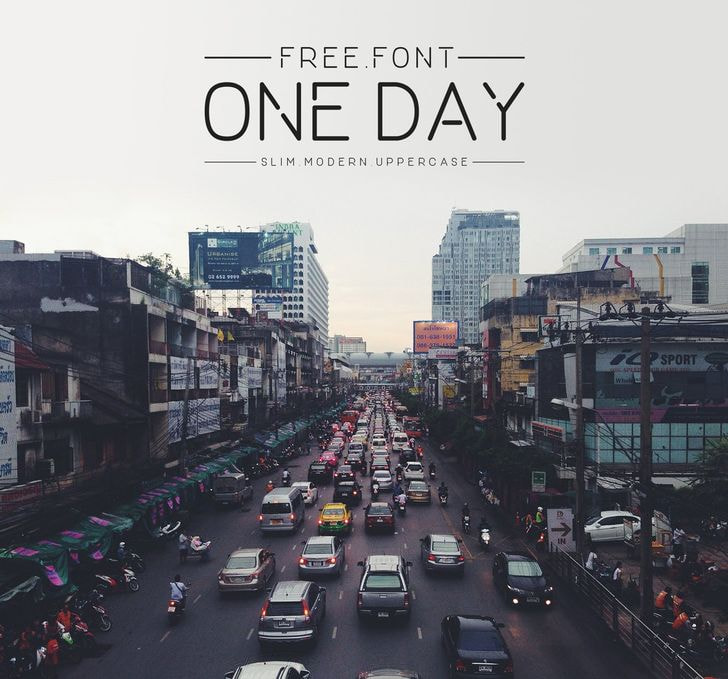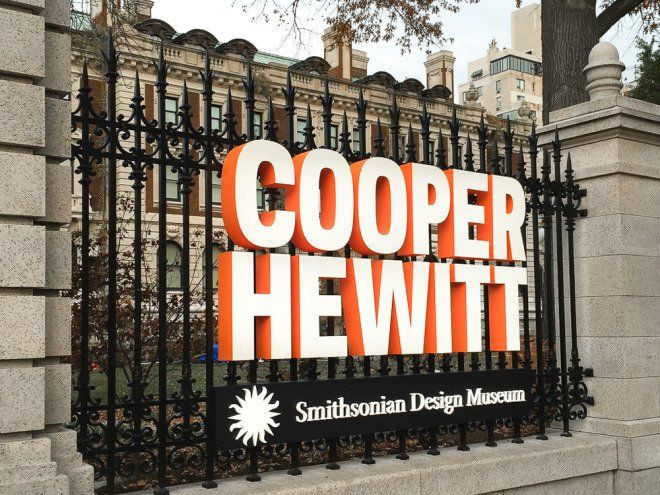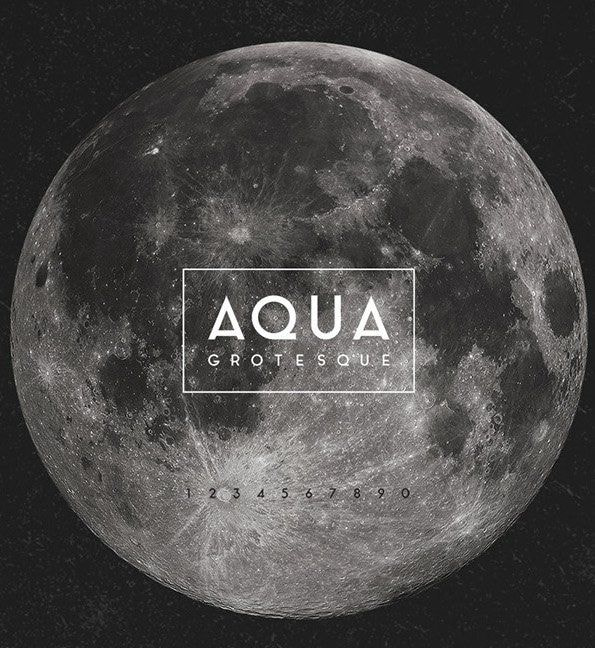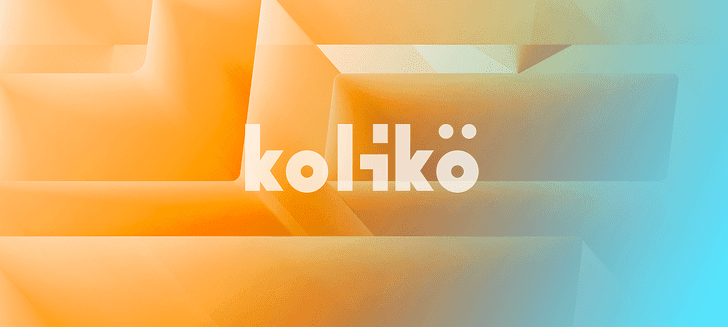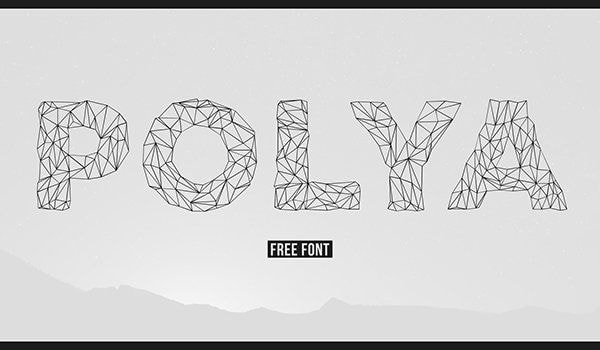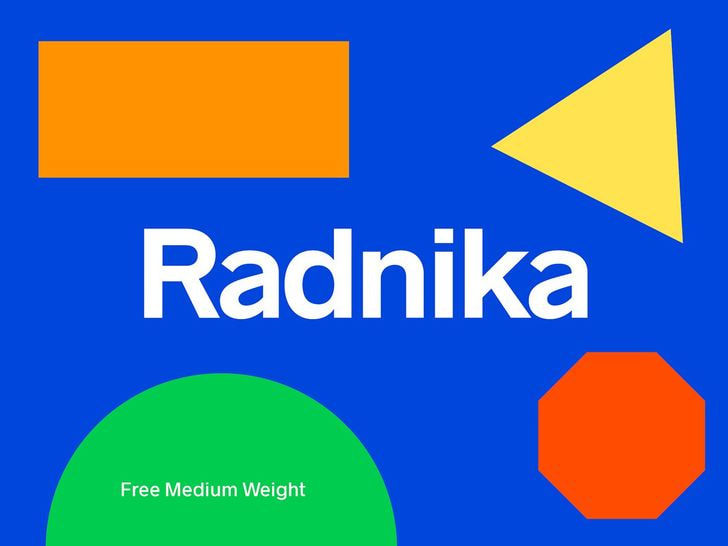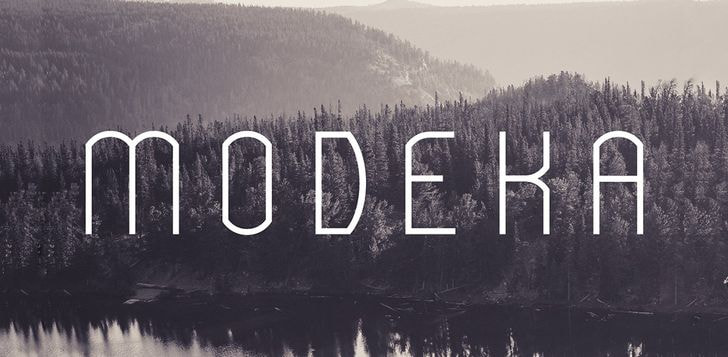
01. Lombok
Anda dapat segera melihat dari 50 font gratis ini bahwa font modern mayoritas adalah tipografi serif; Artinya, tidak ada garis proyeksi atau ikal di ujung huruf. Lombok dari Alexandre Pietre sangat samar dan geometris dengan bentuk yang terbelah dan dua garis.
02. Ailerons
Ailerons adalah font dari Adilson Gonzales de Oliveira Junior yang terinspirasi model pesawat terbang tahun 1940an. Ujung setiap huruf miring dan sedikit melengkung dengan detail yang halus.
03. One Day
One Day adalah font ramping dan huruf besar dari Nawras Moneer. Bentuk font yang bulat dan garis putus-putusnya akan menambahksan daya tarik visual pada judul utama manapun.
04. Cooper Hewitt
Ketika Museum Desain Cooper Hewitt Smithsonian melakukan perbaikan, merevitalisasi bangunan dan identitasnya, dia juga melibatkan perancang Chester Jenkins untuk menciptakan font sans serif kontemporer yang tersedia gratis untuk keperluan umum. Nah, itu adalah desain demokratis.
05. Aqua
Font dari Laura Pol ini memiliki garis lurus yang kontras dengan bentuk yang sangat bulat. Sudut yang kuat mendominasi pada huruf besar sementara lingkaran halus mendominasi huruf kecil.
06. Kolikö
Keluarga font Kolikö dari Fontfirma memiliki karakter Latin dan Cyrillic dalam gaya reguler, tipis, dan tebal. Ini adalah font sans serif geometris dengan struktur bersih untuk berita utama yang tebal.
07. Polya
Adrien Coquet mendesain font Polya yang terinspirasi dari jaring poli-poli, yakni jala untuk pemodelan komputer 3D. Hasilnya adalah font dengan bentuk tebal dan tampilan yang ringan.
08. Radnika
Alfredo Marco Pradil menggambarkan font radnika-nya sebagai "tipe pekerja keras." Ini adalah jenis huruf multi-fungsi yang menjembatani kesenjangan antara tipografi abad ke-19 yang kuat dan ekspresif dan tipografi abad ke-20 yang halus dan buram. Font gaya 'medium' gratis untuk diunduh.
09. Modeka
Modeka dari Gatis Vilaks adalah font ringan dan elegan yang menggabungkan sudut dengan detail yang membulat. Hasilnya adalah set karakter dengan persimpangan yang terlihat antara bagian masing-masing elemen.
10. Higher
Marisa Passos mendesain Higher untuk proyek sekolah setelah itu dia menawarkannya gratis untuk penggunaan umum. Ideal untuk berita utama, Higher memanjang dengan bentuk tampilan setiap hurufnya yang rapat pada bagian atas atau bawah setiap karakter.
11. Nordik
Nordik adalah tipe huruf eksperimental yang didesain oleh Yana Bereziner. Font ini terinspirasi oleh Norwegian runes, yang merupakan huruf yang digunakan dalam berbagai bahasa jerman sebelum adopsi alfabet Latin.
12. Komoda
Komoda adalah font ramping yang dirancang oleh Asia Ang. Font ini cock sebagai jenis huruf untuk berita utama dan judul, dan font ini terlihat cerdas dan modern pada contoh, yang dibingkai dengan garis persegi panjang.
13. Kollektif
Brave New Fonts merancang Brave New Fonts Kollektif sebagai alternatif untuk kontras-rendah tipografi di abad ke-21. Font ini dapat digunakan untuk tampilan dan blok teks, tersedia dua gaya dan dua bobot.
14. Achi
Achi adalah font eksperimental pertama dari Shibu PG. Font ini bergaya modern dan kontemporer serta garis ganda stem dan stroke menambahkan sentuhan detail Art Deco.
15. Parley
Parley, dari Filipe Rolim, memiliki garis diagonal yang menarik yang memotong setiap huruf dan angka; Beberapa potongan itu adalah bagian dari karakter sedang lainnya adalah detail tambahan.
16. Aroma
Laura Pol juga menciptakan font ini, Aroma. Tersedia dalam huruf tebal dan tipis, font ini bergaya kontemporer dengan dengan lengkungan dan terminal siku yang sedikit retro dan sedikit kaligrafi.
17. Boxing
Font Boxing dari Tano Veron memberi pukulan berat dengan bentuknya yang kuat, memanjang, dan rapat. Font ini diberi judul dengan tepat oleh Veron yang terinspirasi oleh poster tinju retro.
18. Minimalust
Dirancang oleh Pratama Yudha, Minimalust adalah font bersih dan minim yang terinspirasi dari tulisan tangan dan cetak vintage. Jenis huruf sans serif memiliki tepi yang halus dan sudut yang membulat.
19. Hyped
Font hyped dari Med Ness menampilkan bentuk geometris dan ruang negatif. Beberapa karakter terinspirasi oleh Art Deco sementara sebagian kecil lainnya dari postmodernis Memphis.
20. Metria
Metria adalah jenis huruf geometris serbaguna yang memiliki sudut konsisten dan lingkaran yang tidak sempurna. Desainer Jake Lunde mengatakan, "Font ini terinspirasi dari bentuk geometris yang kaku yang diinfus dengan kurva organik untuk membuat kata-kata menjadi hidup."
Dirancang oleh Christopher J. Lee, Canter adalah jenis huruf yang semua-kapital dan rapat. Font ini cocok sebagai tampilan untuk judul, berita utama, dan poster.